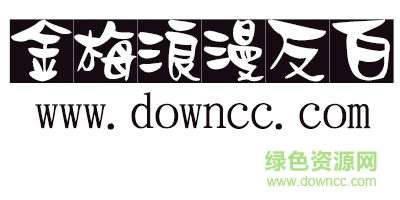
金梅浪漫反白字體輸出的文字效果很個(gè)性,這款字體在設(shè)計(jì)一些大標(biāo)題的時(shí)候還是比較合適的,字體比較醒目,又不失生動(dòng)!歡迎網(wǎng)友們下載體驗(yàn)。
金梅浪漫反白字體是金梅字體庫(kù)里的一款字體,該字體每一個(gè)都是黑底白字,非常適合用于廣告設(shè)計(jì)、雜志報(bào)刊等領(lǐng)域。有喜歡的朋友趕快來綠色資源網(wǎng)下載使用吧!